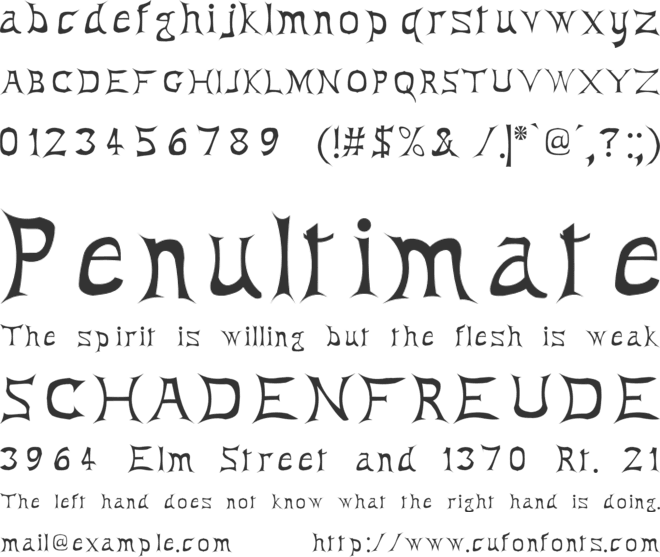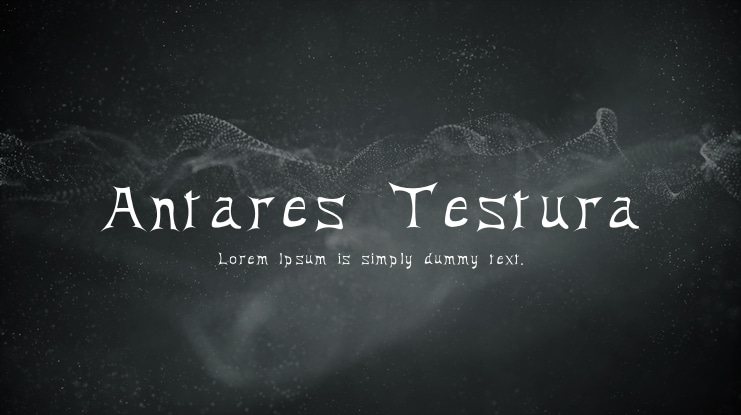
Antares Testura Font Family
P. A. Vannucci
ANTARES font: Dall’origine della scrittura occidentale moderna, un font inedito che unisce la tradizione Humanista con la virtù della scrittura amanuense. Antares è un font Open Type disponibile in 6 formati (Regular-Textura-Rotunda/bold).